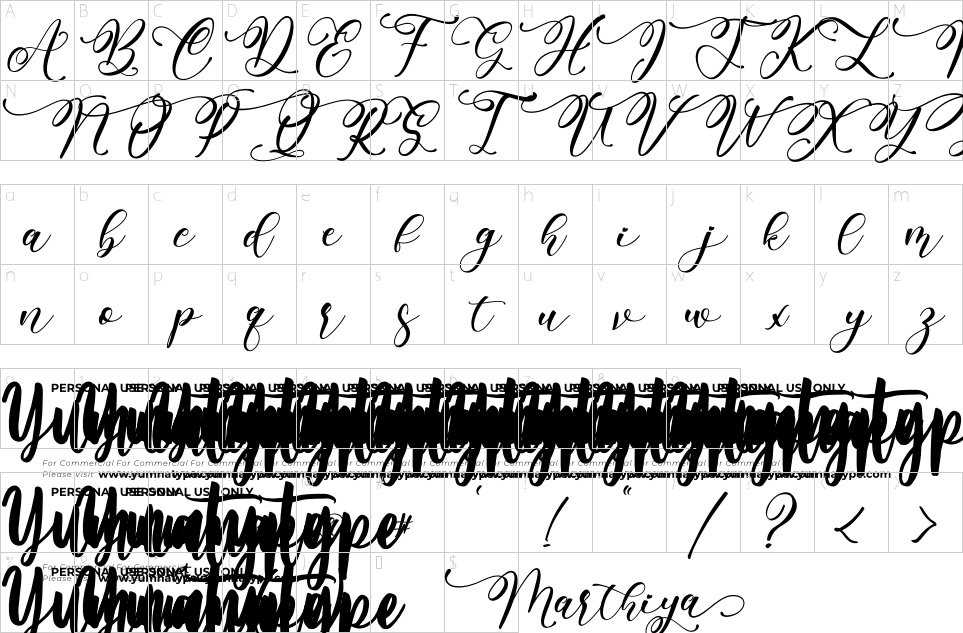
A Marthiya Font é um belo aditivo para suas criações digitais. Desenvolvida pela Yumna Type, esta fonte é perfeita para quem busca um visual elegante e sofisticado. Com apenas dois parágrafos, você pode destacar sua escrita, tornando-a única e imponente. Atualmente, a Marthiya tem sido baixada 3.621 vezes, o que indica seu valor como uma fonte de qualidade. Seja para aplicativos, templates de e-mail ou qualquer projeto digital, a Marthiya é uma escolha óbvia. Combinada com suas outras fontes gratuitas, você pode criar designs impecáveis. Descubra por si mesmo o poder da Marthiya e transforme suas criações digitais em obras de arte.